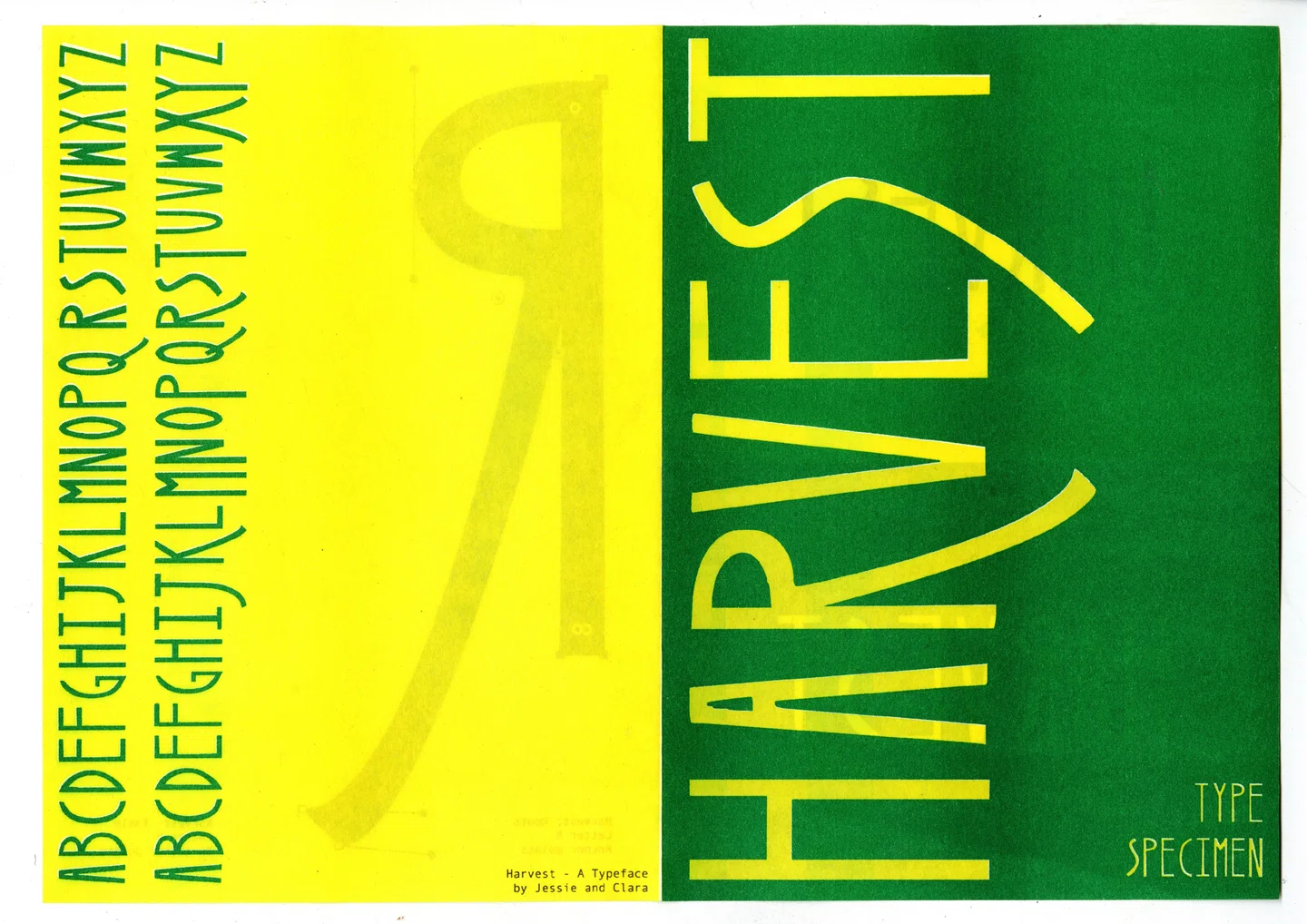
Фирменный стиль Harvest: яркие цвета, ризография и рукописный шрифт
Айдентика отражает главную миссию — превращать приемы пищи в значимые ритуалы
По словам графических дизайнеров и соучредителей Harvest Джесси Коллинз и Клары Холмс, приготовление еды и проектирование — это не две разные вещи: «И то, и другое — форма общения, основанная на повествовании», — говорит Джесси. Наши студии, как и наши кухни, — это «пространства для тестирования и создания, все сформированные нашим личным опытом и исследованиями».
Развивая интерес ко всему, что связано с едой, во время учебы в Университете Фалмута, пара создала совместный коллективный и продолжающийся проект: Harvest, который исследует все, что входит в процесс совместного приема пищи.
Их итоговое сотрудничество — Harvest — направлено на исследование «как мы едим и что мы едим» посредством еды и общественных семинаров. Проект, который возник из естественной паузы от стремительного городского образа жизни (где обеденные перерывы исчезли, и мы едим все, что удобно, за нашими офисными столами).
Графическая идентичность для всех этих искусных кулинарных начинаний должна была передавать «чувство связи между людьми, землей и процессами выращивания и обмена едой», говорит Клара. Чтобы достичь этого, дуэт «разработал систему дизайна, которая отражает укоренившиеся качества фермерства и общественных собраний».
Начав с типографики, Клара и Джесси работали над вырезанными вручную формами букв, прежде чем остановились на нарисованном вручную шрифте Harvest, представленном в двух вариантах: один был вдохновлен органическими формами корней растений, а другой — смелыми ножками стола.